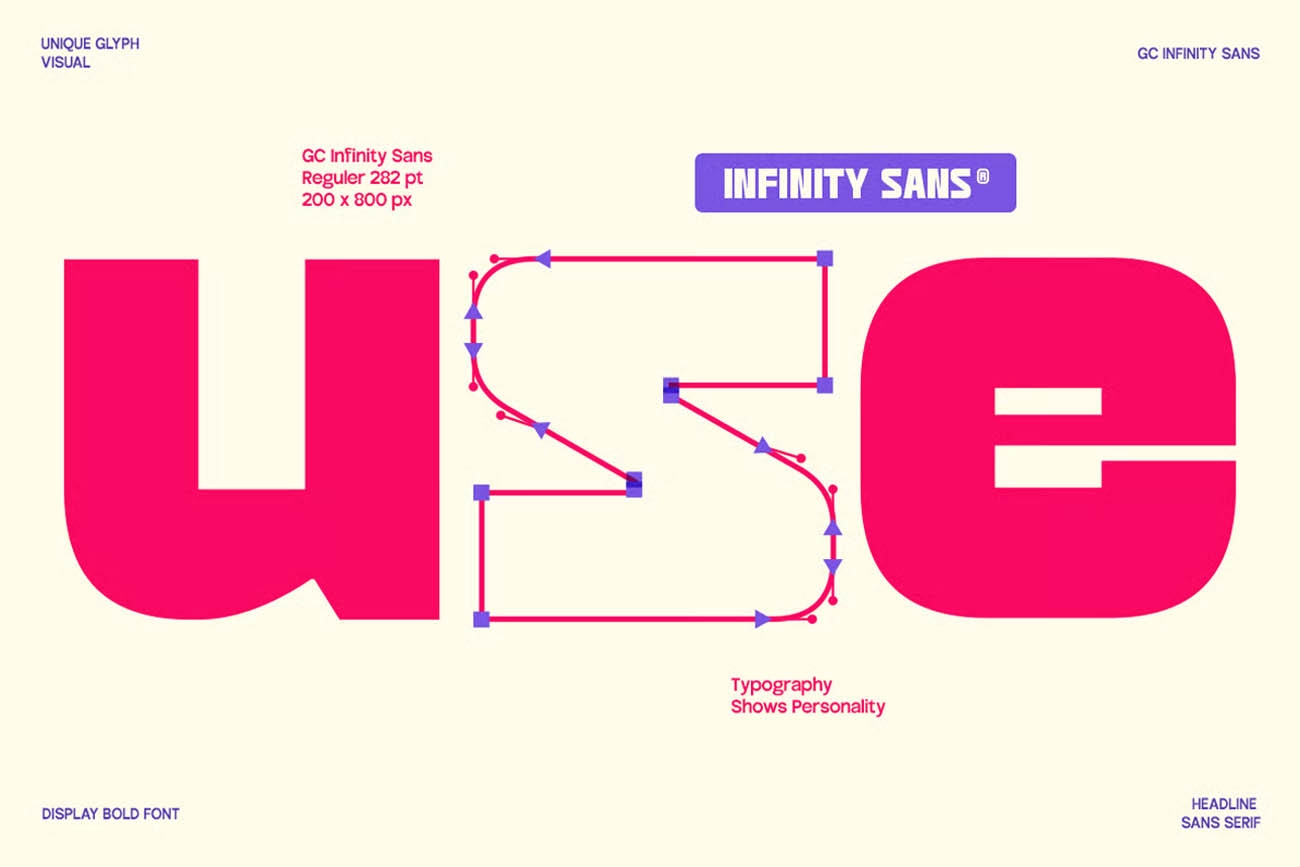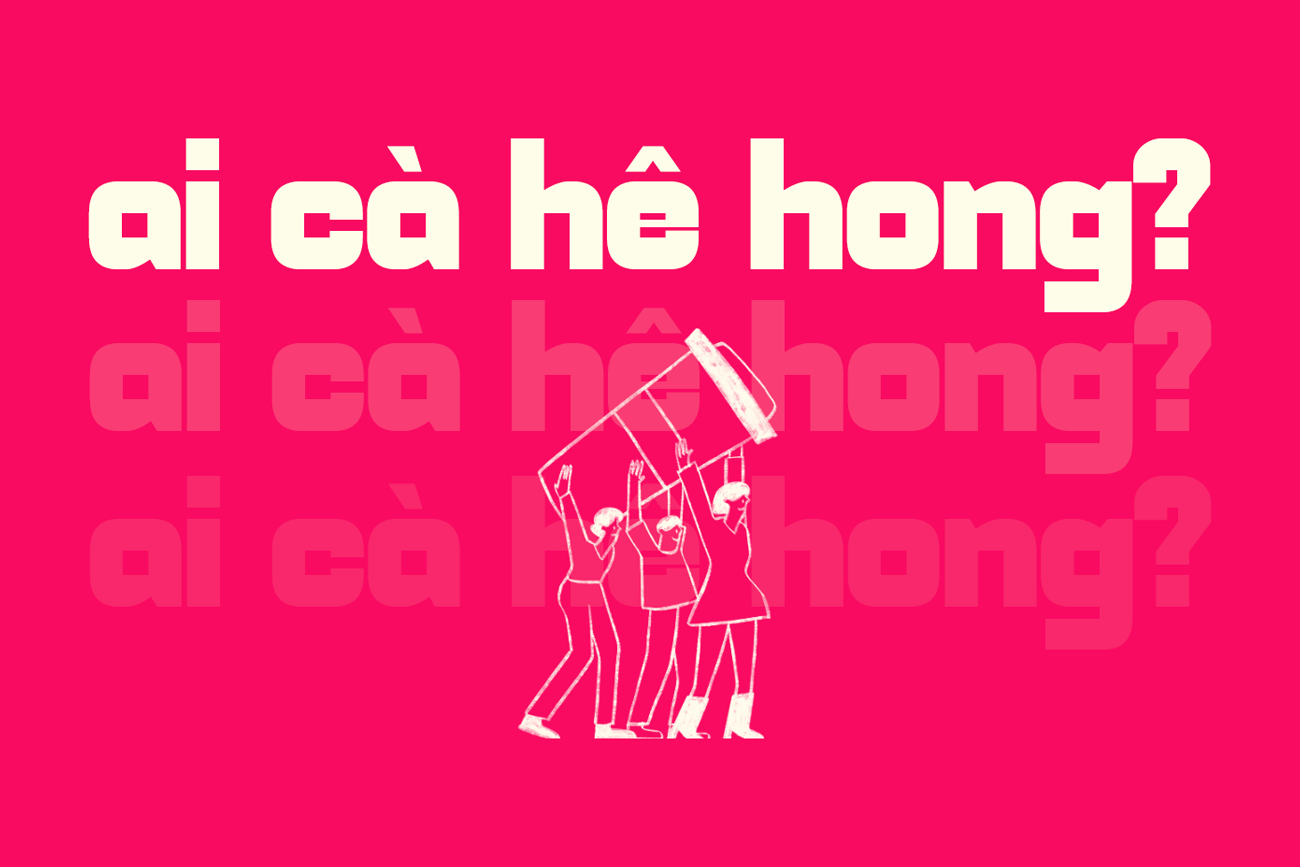
Font Display Cứng Cáp Cho Thiết Kế - TH Infinity Việt Hóa
Trong thế giới Typography hiện đại, việc tìm kiếm một kiểu chữ vừa mang tính thẩm mỹ cao, vừa truyền tải được sức mạnh nội tại của thương hiệu là ưu tiên hàng đầu của các Designer. Hôm nay, chúng tôi xin giới thiệu đến cộng đồng sáng tạo bộ font việt hóa TH Infinity – một bản chuyển ngữ hoàn hảo từ tác phẩm gốc đình đám của Glyphonic.
Vẻ đẹp mạnh mẽ từ nguyên bản Infinity
Được sáng tạo bởi Glyphonic, Infinity là một bộ font Display Bold Sans mang đậm hơi thở của thời đại số. Ngay từ cái nhìn đầu tiên, Infinity đã gây ấn tượng mạnh bởi cấu trúc hình học vững chãi, các đường nét dày dạn và dứt khoát.
Đây là sự lựa chọn lý tưởng cho những ai đang tìm kiếm một **font cứng cáp** để thể hiện sự uy quyền, tính ổn định và sự chuyên nghiệp. Không quá cầu kỳ trong các chi tiết trang trí, Infinity tập trung vào tính dễ đọc và khả năng gây chú ý ngay lập tức, khiến nó trở thành "vũ khí" hạng nặng cho các tiêu đề (headline), poster quảng cáo, hoặc logo thương hiệu thể thao và công nghệ.
TH Infinity: Bản Việt hóa chỉn chu từ Team TH
Nhận thấy tiềm năng ứng dụng to lớn của Infinity tại thị trường Việt Nam, đội ngũ TH đã tiến hành Việt hóa bộ font này với tên gọi TH Infinity. Quá trình Việt hóa không chỉ đơn thuần là thêm dấu, mà là sự cân chỉnh tỉ mỉ về khoảng cách (kerning) và vị trí các dấu câu sao cho hài hòa nhất với tổng thể bộ chữ gốc.
Sử dụng phiên bản font việt hóa này, các Designer sẽ không còn gặp tình trạng lỗi dấu khó chịu hay sự lệch lạc về tỷ lệ khi gõ Tiếng Việt. Các dấu mũ, dấu ngã, dấu hỏi được thiết kế tinh tế, giữ nguyên tinh thần mạnh mẽ và hiện đại mà Glyphonic đã xây dựng.
Ứng dụng thực tế
Với đặc tính là một font cứng cáp và nổi bật, TH Infinity phát huy tác dụng tốt nhất khi được sử dụng ở kích thước lớn. Bạn có thể ứng dụng bộ font này cho:
• Tiêu đề Poster phim hành động hoặc sự kiện thể thao.
• Banner quảng cáo sản phẩm công nghệ.
• Thiết kế bao bì sản phẩm cần sự nam tính, mạnh mẽ.
• Typography cho áo thun (T-shirt design) hoặc trích dẫn truyền cảm hứng.